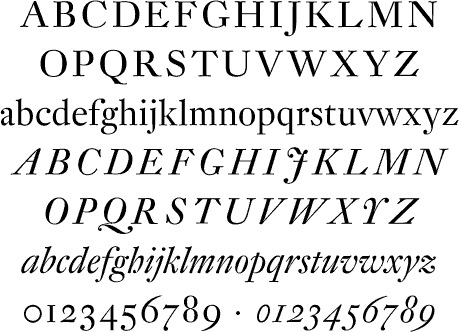
Johann Michael Fleischmann (1701-1768)Gravador de punções alemão que trabalhou na Holanda. As suas letras já mostram contrastes que iriam caracterizar o estilo neo-clássico de Bodoni e Didot.
Tipógrafo e gravador de punções alemão, nascido em Nürenberg, emigrado para os Países Baixos. Óptimo técnico, foi autor de letras romanas e itálicas de caracter barroco. Em 1730 gravou punções que podem ser considerados de estilo rocóco, usando aço e levando a técnica aos seus limites. Conseguiu assim atingir traços finíssimos e uma qualidade especial de brilho na folha impressa (sparkle). Fleischmann trabalhou largos anos para a empresa dos Enschedé em Haarlem. A maior parte do material tipográfico de Fleischmann que sobreviveu está guardado no Enschedé Museum em Harlem.
FontesAs fontes de Fleischmann inspiraram gerações de typeface designers. Nos seus tempos, foi imitado por Pradell, um gravador de punções que trabalhou para Ibarra.
Entre os typeface designers contemporâneos, Mário Feliciano (fonte Eudald e fonte Expresso) e Andres Balius (fonte Pradell). As letras de Fleischman serviram também de modelo à fonte Farnham, que foi distinguida na Exposição de 2004 do Type Directors Club. |